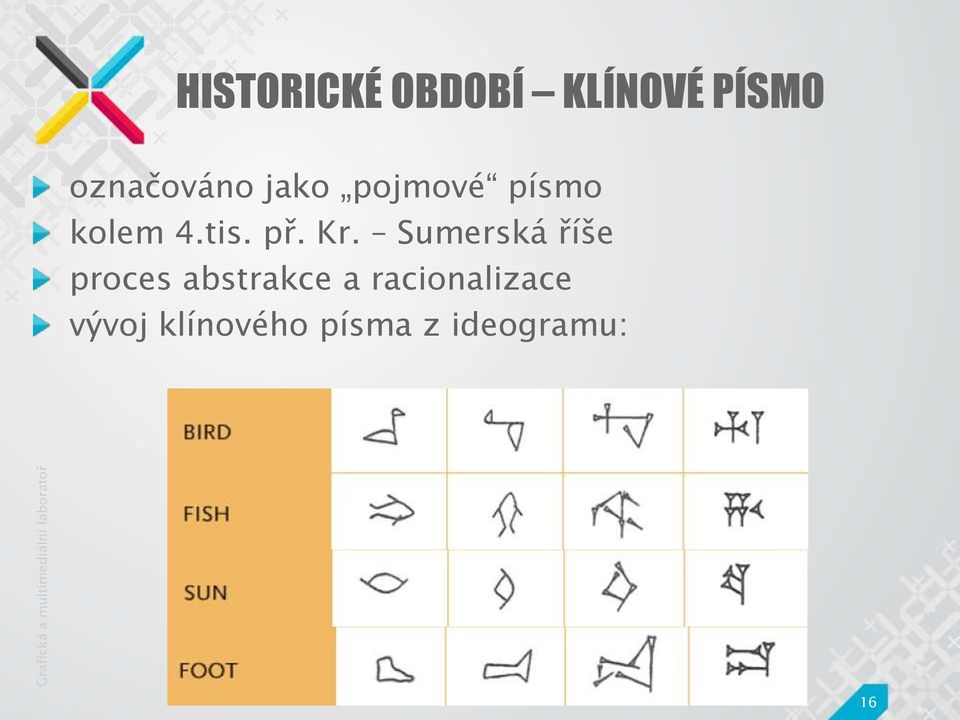
2 CO JE PÍSMO? Písmem rozumíme znaky, které mají sloužit k trvalému zaznamenávání myšlenek a skutečností. Je časově i místně nezávislé na osobě sdělujícího. Předpokladem pro přečtení písma a porozumění obsahu je nejen znalost písem (znaků), ale i znalost řeči (jazyka), v níž je písmo napsáno. 2
3 PROČ VZNIKLO PÍSMO? činnost lidí a společenský charakter práce - ústní (příp. vizuální) forma výměny informací nestačila vývoji v ostatních oblastech lidského života umožnilo komunikaci mezi lidmi umožnilo i přenos, uchovávání, a prezentaci informací lze naslouchat našim předchůdcům lze uchovávat myšlenky a poznatky našich současníků rozvoj vědy, vzdělanosti a ve všeobecném měřítku i lidský pokrok je produktem tvořivého myšlení jednotlivých generací písmo jako grafický znak jazyka je projevem vyšší kultury jakéhokoliv národa a počátkem jeho historického období písmo má i hodnotu estetickou a je výrazem určitého vkusu 3
4 MEZNÍK VE VÝVOJI LIDSTVA? končí středověk a začínají se psát novodobé dějiny lidstva vynález nejpodstatněji zasáhl do vývoje lidské kultury princip: odlévání liter ze speciální slitiny, ruční sestavování textu obraz písma na papír pomocí ručního lisu (vlastní tisk) 4
5 HISTORICKÉ ROZDĚLENÍ PÍSMA obrázkové (piktografické) stylizované obrázky předmětů pro dorozumívání mezi kmeny slovní (ideografické, pojmové) obrázek se začal spojovat s konkrétním slovem, nikoli předmětem k této změně došlo nezávisle na sobě ve starém Egyptě, v říši Mayů ve Střední Americe a v Mezopotámii nejstarší egyptské hieroglyfy se později začaly spojovat se slabikami (zvuky slov) slabikové hláskové 5
6 HISTORICKÉ ROZDĚLENÍ PÍSMA obrázkové (piktografické) slovní (ideografické, pojmové) slabikové v Číně - každý znak má dvě části - část se vztahuje k významu a část k výslovnosti arabské písmo - samohláska se vyrozumí z kontextu hláskové (abecední) dnes ho používá většina jazyků 6
7 HISTORICKÉ ROZDĚLENÍ PÍSMA obrázkové (piktografické) slovní (ideografické, pojmové) slabikové v Číně - každý znak má dvě části - část se vztahuje k významu a část k výslovnosti arabské písmo - samohláska se vyrozumí z kontextu hláskové (abecední) dnes ho používá většina jazyků speciality Např.: Morseova abeceda, Braillovo písmo,... 7
8 VZNIK PÍSMA Historie písma
9 PŘEDHISTORICKÉ OBDOBÍ - KRESBY První kresby asi před lety, ale první písmo až o let později => vznik písma je dlouhý a složitý proces. Petrograph Kresby namalované na skalní stěny 9
10 PŘEDHISTORICKÉ OBDOBÍ - KRESBY První kresby asi před lety, ale první písmo až o let později => vznik písma je dlouhý a složitý proces. Petrograph Petrogramy skupina informačních prostředků, která předcházela vzniku písma. jsou to různým způsobem sestavené či navršené kameny či jiné předměty určitým uspořádáním dávají určitý smysl, často na základě dohody. 10
11 PŘEDHISTORICKÉ OBDOBÍ - KRESBY První kresby asi před lety, ale první písmo až o let později => vznik písma je dlouhý a složitý proces. Petrograph Petrogramy Petroglyfy Kresby a piktogramy vytvořené odstraněním částí skalního povrchu 11
12 PŘEDHISTORICKÉ OBDOBÍ - MNEMOGRAMY grafické či jiné pomůcky sloužící k zapamatovávání (mnemotechnické pomůcky), např: Vlastnické značky Dobytek, otroci a spol Zpravodajská hůl Pomalovaná dohodnutými symboly a barvami a posel s ní objížděl zemi a vyhlašoval válku, pozvání na lov, taneční slavnost, oznámení rodinné události, prosbu o pomoc 12
13 PŘEDHISTORICKÉ OBDOBÍ - MNEMOGRAMY grafické či jiné pomůcky sloužící k zapamatovávání (mnemotechnické pomůcky), např: Uzlové znaky Nepřesně nazývané uzlové písmo. Ve skutečnosti to byly pomůcky sloužící k zapamatování číselných údajů Calculi kameny s geometrickými značkami, které sloužily k zapamatování kalkukace, kalkulačka,calcul, 13
14 PŘEDHISTORICKÉ OBDOBÍ - PIKTOGRAMY schématický obrázek reálného předmětu, už to není pouhá skalní kresba piktogramy vyjadřovaly konkrétní věci, ale dovedly také označit abstraktní pojmy srozumitelné téměř všem bez ohledu na jazyk z piktogramů se postupně vyvíjely ideogramy 14
15 PŘEDHISTORICKÉ OBDOBÍ - IDEOGRAMY z piktogramů se postupně vyvíjely ideogramy vzniká spojením několika piktogramů (dvou i více) jeden obrázek označuje zároveň jedno slovo, častěji i jednu celou větu, myšlenku, jednotlivý moment ještě neváže k určité zvukové podobě slova, ale k pojmu (idei), který slovo představuje. Proto se písmu říká pojmové (ideografické, pojmové) z piktogramů a ideogramů se v příhodných podmínkách začalo tvořit písmo 15
16 HISTORICKÉ OBDOBÍ KLÍNOVÉ PÍSMO označováno jako pojmové písmo kolem 4.tis. př. Kr. Sumerská říše proces abstrakce a racionalizace vývoj klínového písma z ideogramu: 16
17 HISTORICKÉ OBDOBÍ HIEROGLYFY složitějšími ideogramy jsou hieroglyfy. jednotlivé značky se začaly vztahovat ke zvukům slov vznikají pravidla, které určovaly, zda znak označuje zvuk či předmět abeceda se z egyptského písma nikdy nestala 17